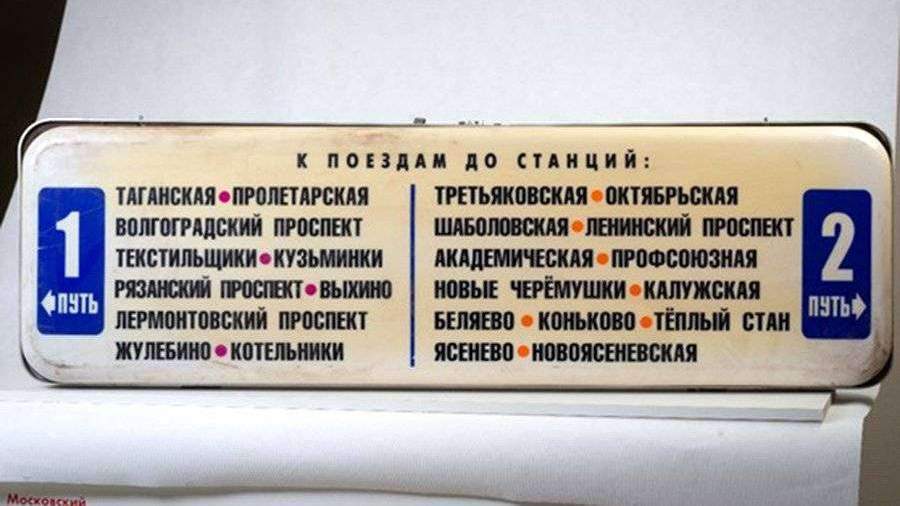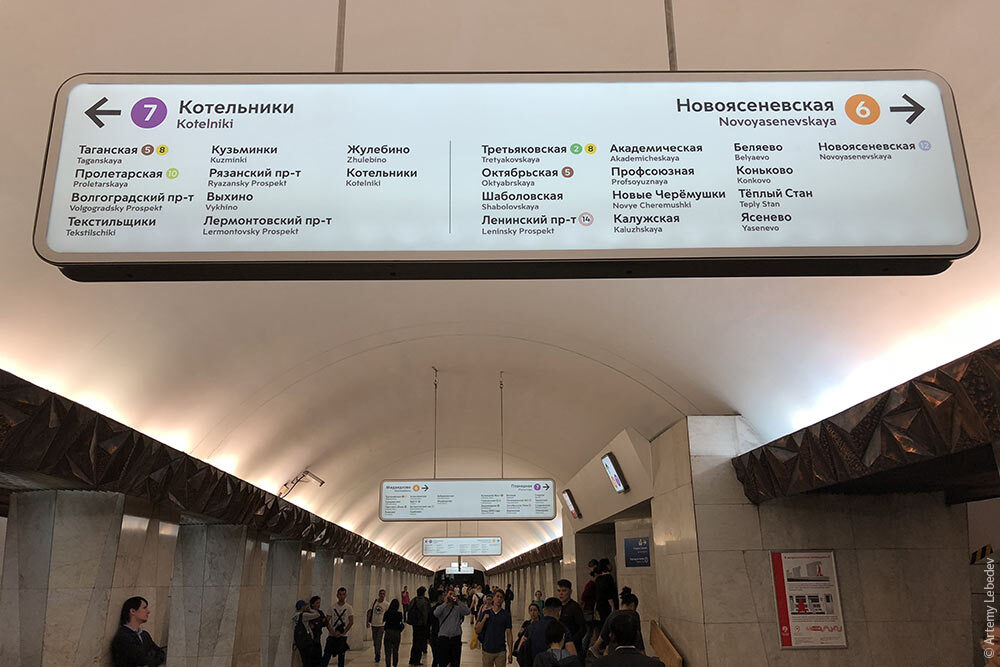
Шрифт крупнее⁠⁠
С годами стала очевидна одна очень простая вещь. Глаза не становятся острее, здоровья не прибавляется.
Поэтому нужно тупо увеличить размер шрифта везде - на компе, на ноуте, на смартфоне.
И жизнь станет легче примерно сразу.
Всё так. Но сразу возникает вопрос: а кто поменял шрифт на указателях в московском метро на мелкое нечитаемое говно, а? Кто это был? ))